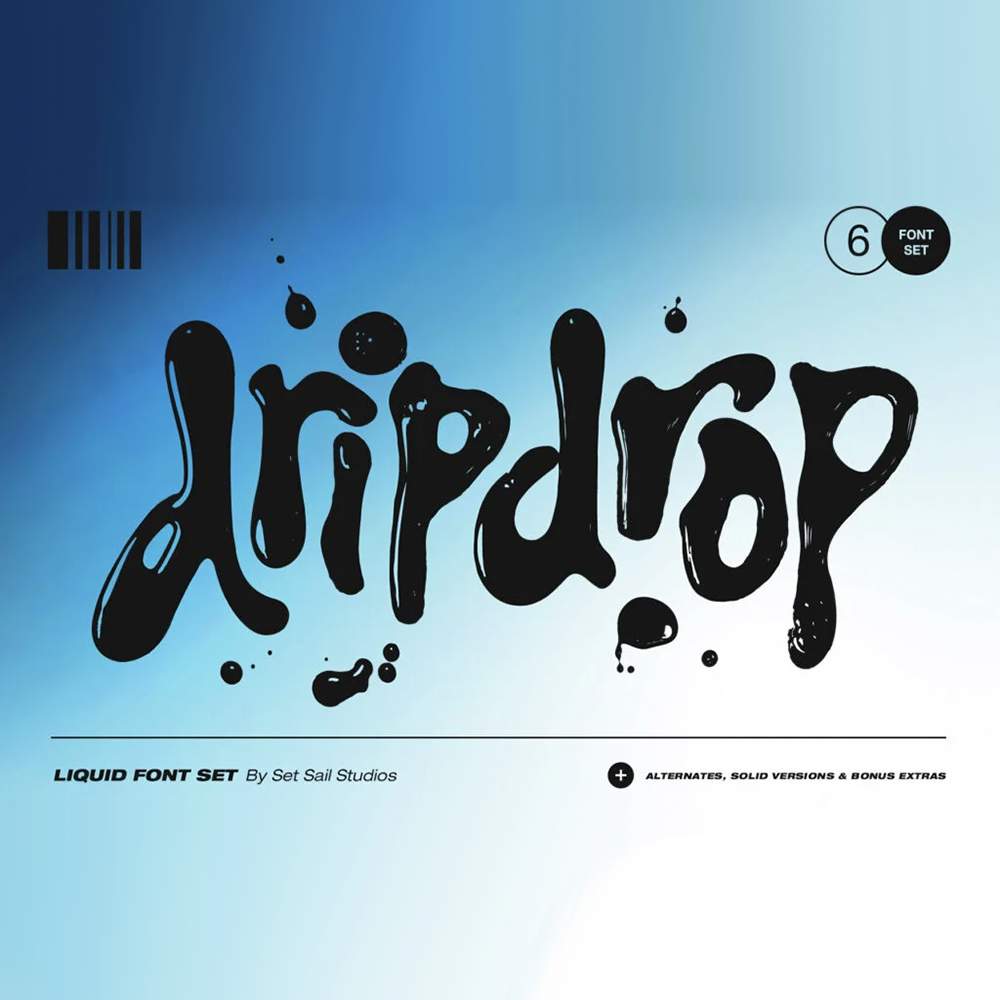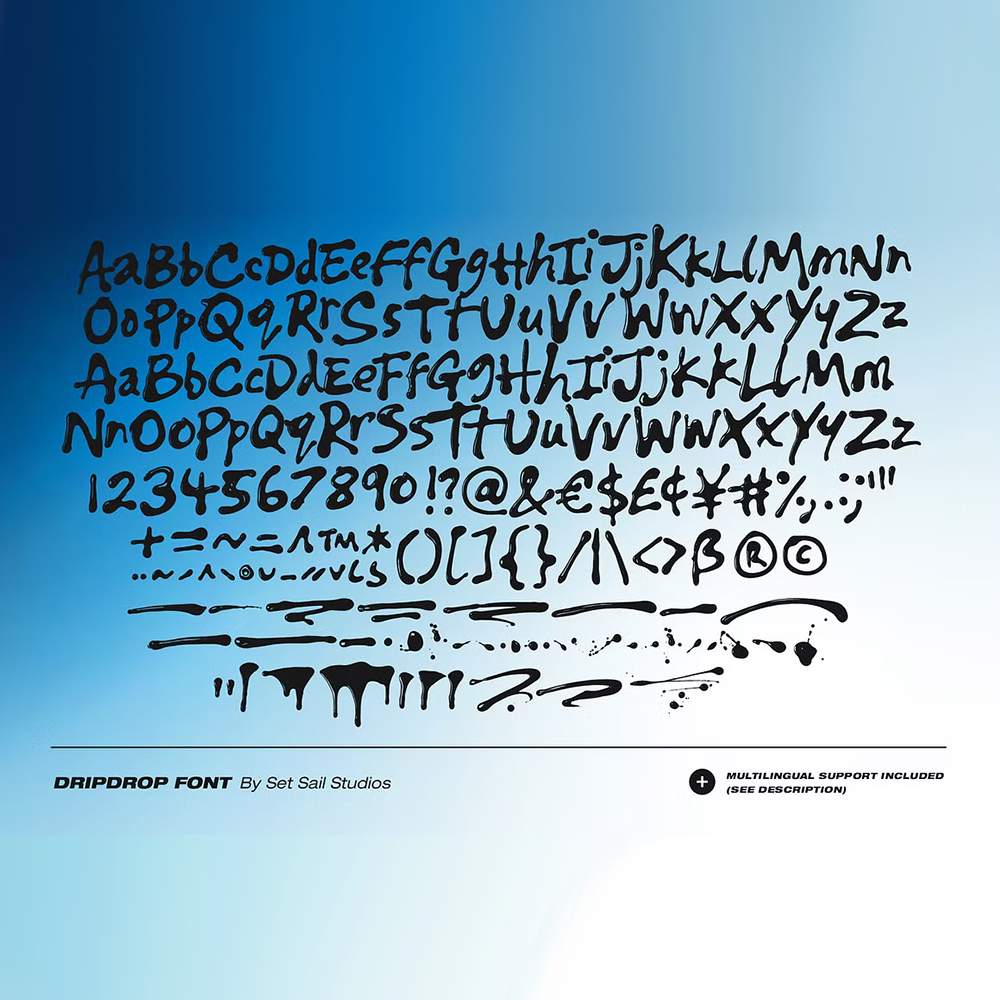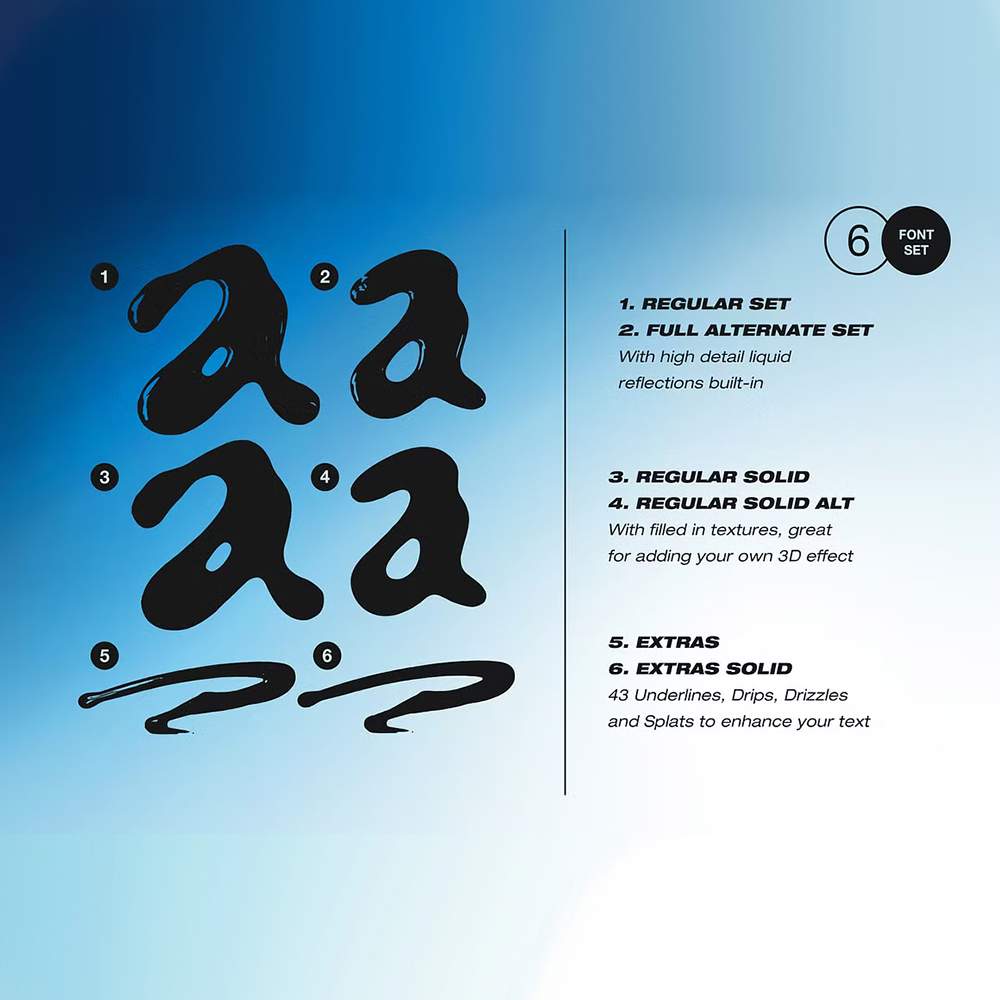
مجموعه فونتهای مایع Dripdrop مجموعهای جسورانه و رسا است که با جوهر مایع واقعی ساخته شده تا انرژی خام و غیرقابل پیشبینی بودن را به طرحهای شما بیاورد. این مجموعه با 6 فونت منحصر به فرد (شامل 2 مجموعه کاراکتر، فونتهای اضافی با قطرات و اسپلاتها و نسخههای جامد) برای گرافیکهای الهام گرفته از Y2K، برندسازیهای جسورانه، پوسترهای سرکش یا رندرهای سهبعدی سفارشی عالی است. چه به دنبال هرج و مرج باشید و چه خلاقانه، Dripdrop تایپوگرافی نمایشی با تأثیر بالا را با رویکردی دستساز ارائه میدهد.